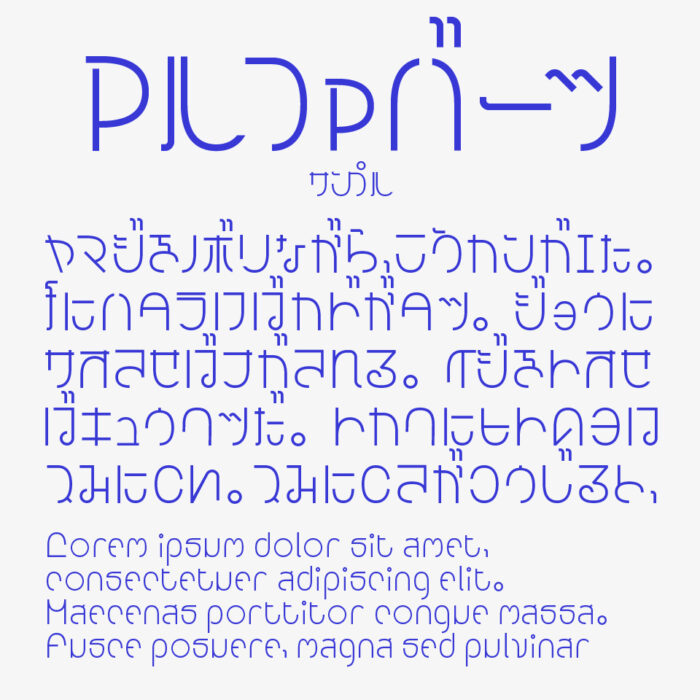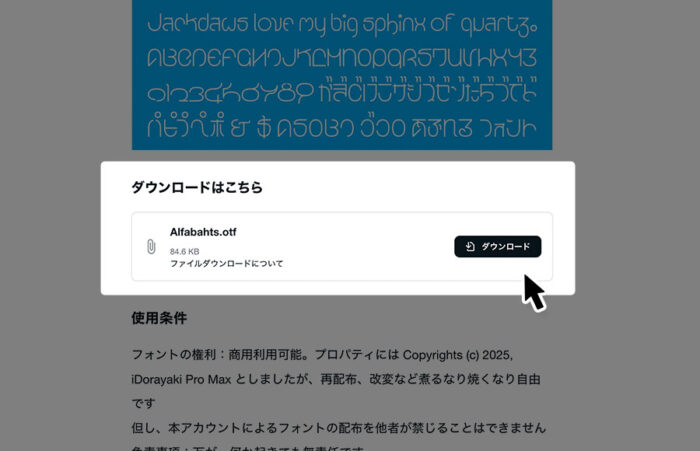
アルファバーツ(Alfabahts)フォントは、タイ語のように見える遊び心のあるデザインフォントです。
「これはタイ語かな?英語かな?日本語かな?」と見る人を少し戸惑わせる面白い仕掛けになっており、近代的なタイ語フォントの特徴をうまく取り入れてたデザインのフォントです。
異国的な雰囲気がありつつポップな印象を与え、ユニークで個性的なビジュアルや表現を作りたい時にぴったりなフォントです。
収録文字は、ひらがな・カタカナ・アルファベット・数字・記号が収録されています。